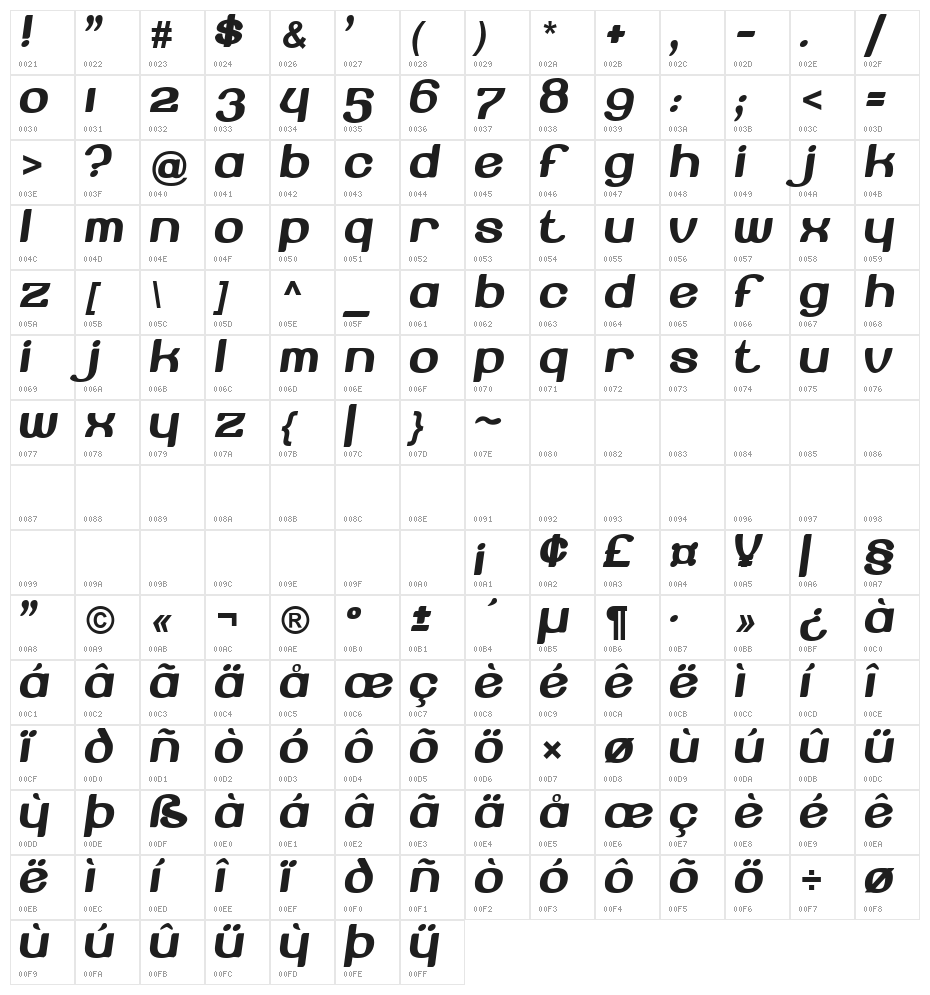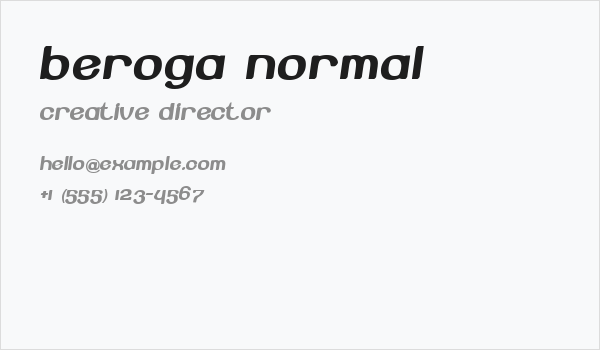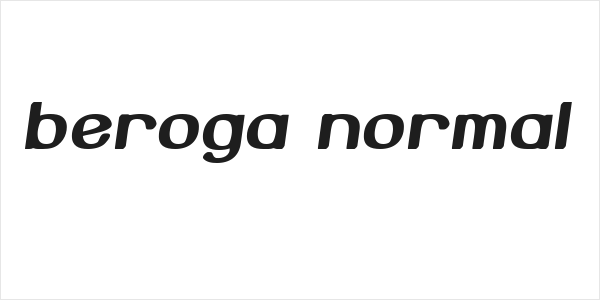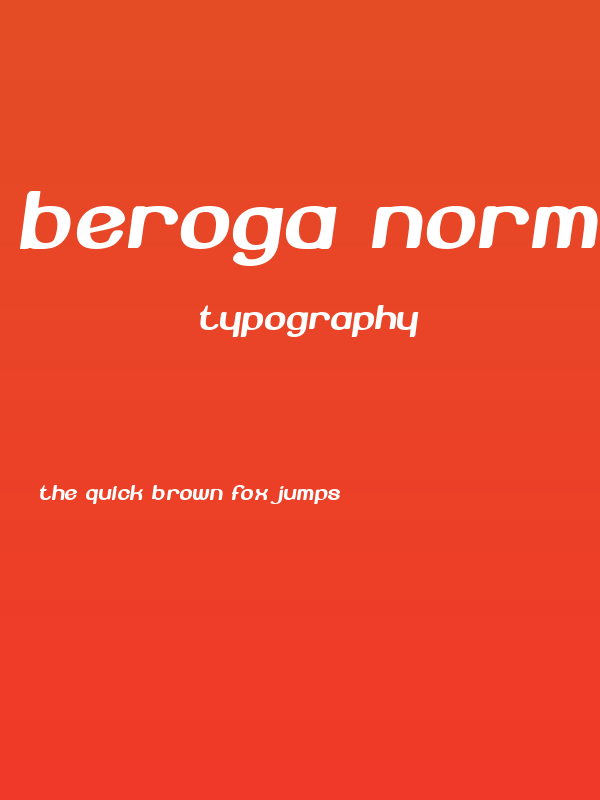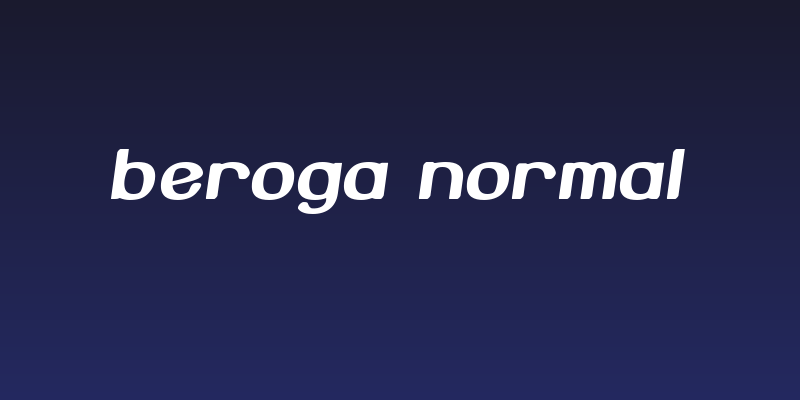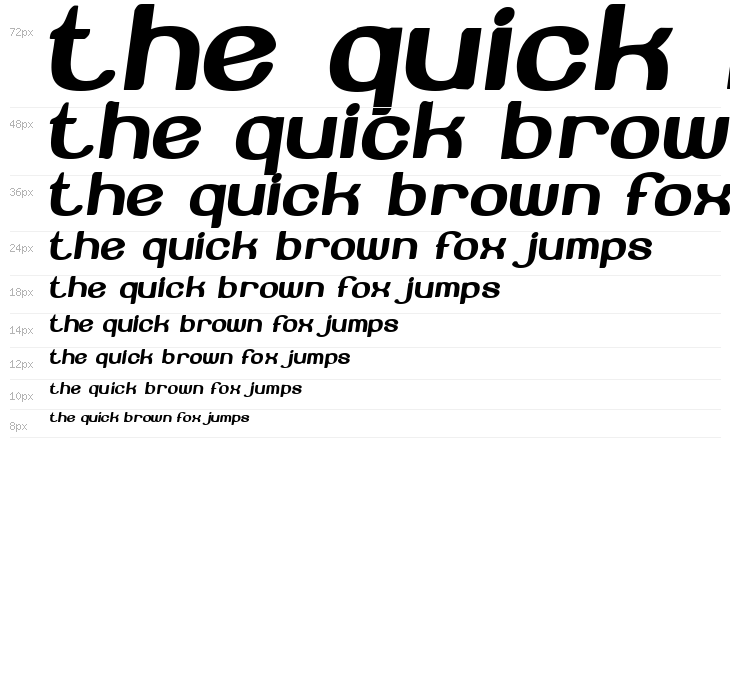
Beroga Normal Font
| Vorgeschlagene Projekte | Ideal for branding, advertising, posters, and headlines where a strong, modern presence is desired. |
Beroga Normal